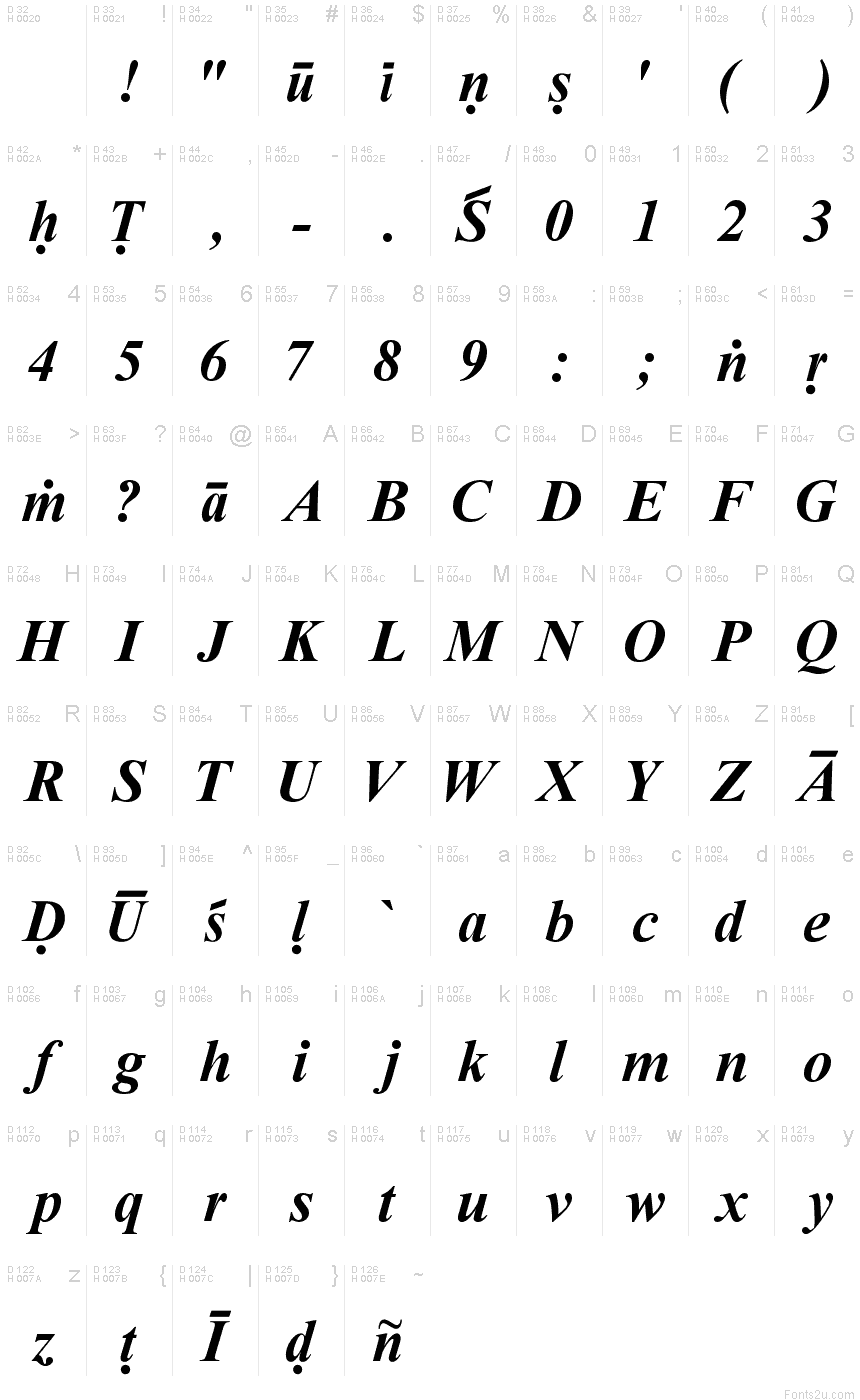
Sanskrit  Roman Bold Italic
Sanskrit Roman Bold Italic to darmowy, kontrastowy krój kursywny z szeryfami, utrzymany w dostojnym, klasycznym stylu. Litery pochylają się z kaligraficznym rozmachem, łącząc ostre, klinowate szeryfy z szerokimi łukami i zwężającymi się łączeniami, co nadaje alfabetowi formalny, literacki rytm, zamiast nowoczesnej dynamiki.
Ten bezpłatny font sprawdzi się na obwolutach książek, w nagłówkach magazynów, na plakatach muzealnych czy galeryjnych, zaproszeniach oraz w brandingu, który wymaga kulturalnego, lekko historycznego akcentu. Doskonale nadaje się również do tytułów i inicjałów, gdzie skośny ruch i wyraźny kontrast nadają krótkim słowom i literom ceremonialny, niemal wygrawerowany charakter.